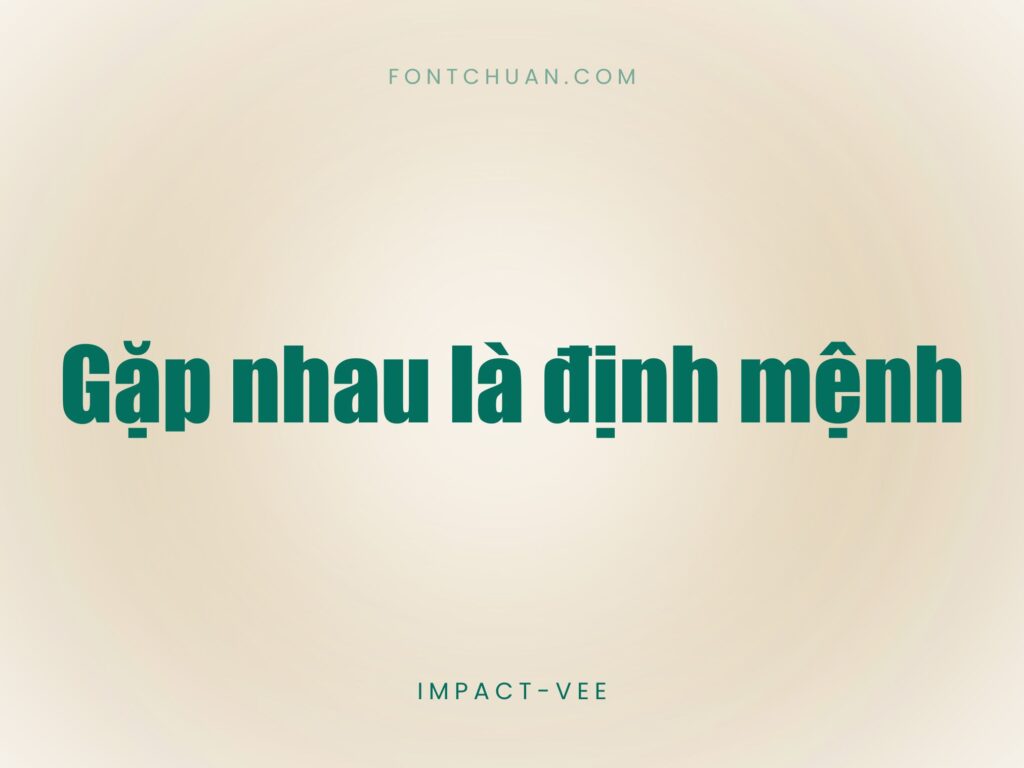
Font Impact Vee Việt Hóa
Tác giả Font: Geoffrey Lee
Việt hóa bởi: Catterio (Mình)
Impact là một Font sans-serif nổi tiếng, được thiết kế bởi Geoffrey Lee vào năm 1965 và phát hành bởi xưởng đúc chữ Stephenson Blake. Phông chữ này nổi bật với các nét dày và đậm, tạo ra sự thu hút mạnh mẽ trong các thiết kế. Về đặc điểm thiết kế, Impact có cấu trúc chữ cái đậm và hẹp, với khoảng cách giữa các chữ cái nhỏ, giúp tạo ra sự nổi bật và dễ đọc ở kích thước lớn. Chính vì thế, Impact còn được xếp vào nhóm Font Display, chuyên dùng cho các thiết kế tiêu đề, poster hoặc banner cần gây ấn tượng thị giác mạnh.
Về ứng dụng, Impact phù hợp cho các thiết kế như tiêu đề, banner, poster và các ấn phẩm quảng cáo khác. Phông chữ này cũng thường được sử dụng trong các meme trên internet nhờ vào sự đơn giản và khả năng truyền tải thông điệp mạnh mẽ. Về ngành nghề, Impact đặc biệt phù hợp với lĩnh vực quảng cáo, công nghệ, giáo dục và các ngành công nghiệp sáng tạo, nơi cần sự thu hút và ấn tượng mạnh mẽ trong thiết kế.